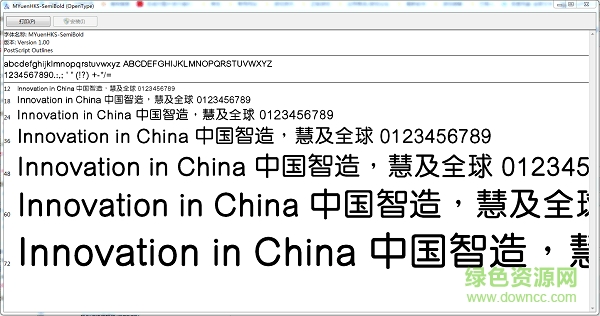
蒙納簡(jiǎn)圓黑二體是一款非常圓潤(rùn),好看的圓形字體,相信這款字體效果是很多女孩子喜歡的,讓你在書(shū)寫(xiě)電子書(shū)信或者進(jìn)行文字排版時(shí)多一種字體類(lèi)型的選擇,其表現(xiàn)形式也很有特色,相信你肯定會(huì)喜歡的,歡迎來(lái)綠色資源網(wǎng)下載使用哦。
1.完全支持日文、韓文、繁體中文和簡(jiǎn)體中文。
2.筆形方頭方尾、黑白均勻。
3.可用于手機(jī)、平板、或者桌面的用戶(hù)界面、網(wǎng)頁(yè)瀏覽或者電子書(shū)閱讀等等。